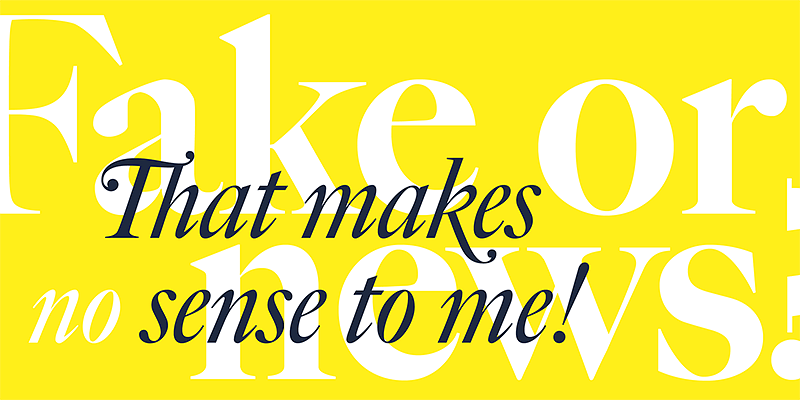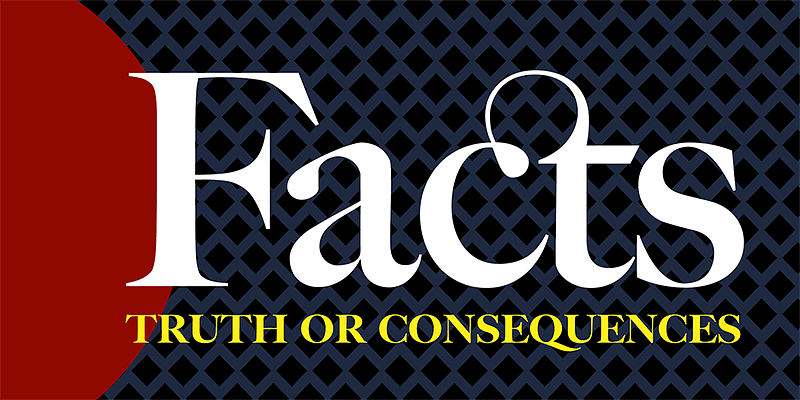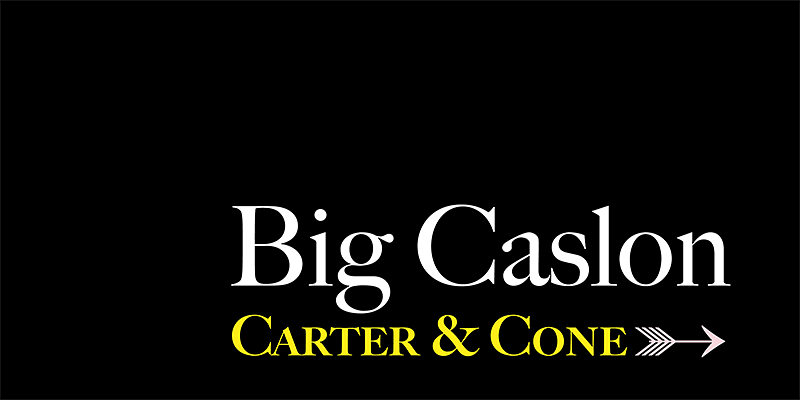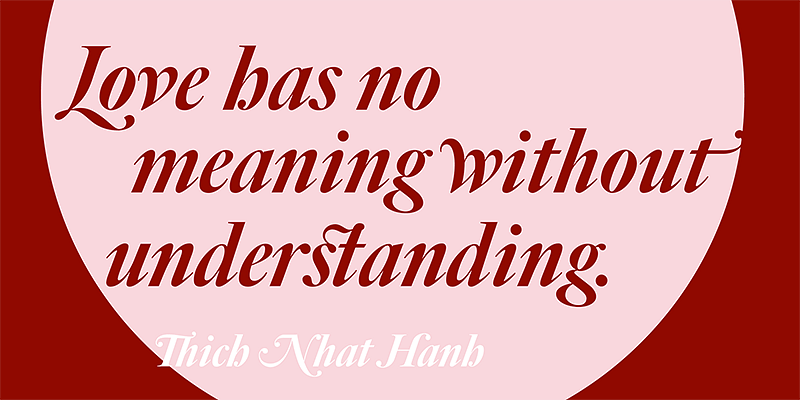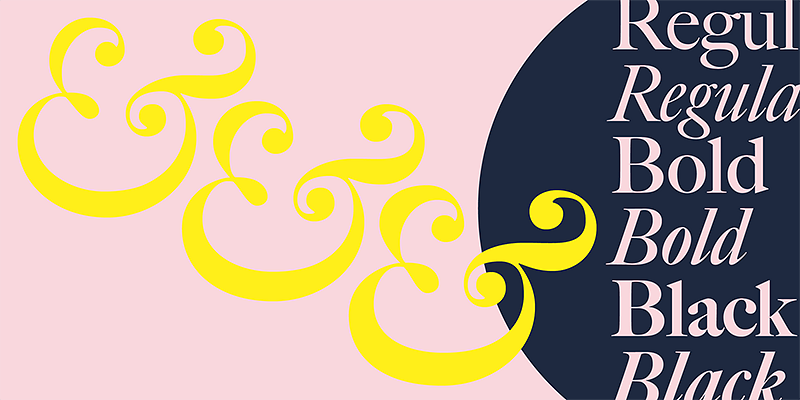
Carter & Cone hat einige der berühmtesten Schriften der Welt und preisgekrönte kundenspezifische Schriften entworfen. Elegant, ausgewogen, nützlich: diese Worte beschreiben die Schriften, die im Rahmen der Partnerschaft zwischen Matthew Carter und Cherie Cone entstanden sind. Während ihre frühen Arbeiten das Fundament der modernen Typografie bilden, bereichern und erweitern ihre neueren Schriften weiterhin die Typografie. Die Konsistenz und Gründlichkeit ihrer Designs ist ein direktes Ergebnis ihrer frühen Ausbildung in Branchen ohne „Rückgängig-Funktion“ wie Stempelschneidekunst und Kalligrafie.